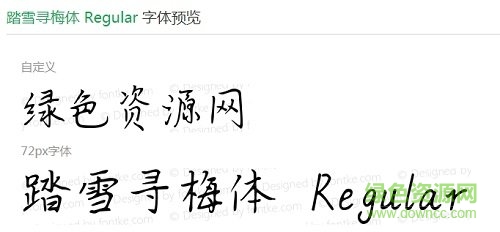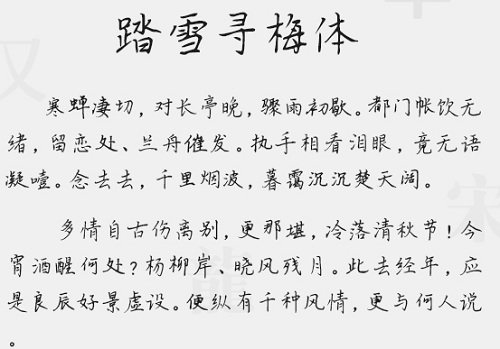
踏雪尋梅體是一款非常完整的中文簡體,采用了手寫字體和硬筆書法的藝術(shù)美感,文字端正不阿,筆畫有序而有力,閱讀清晰大氣,綠色資源網(wǎng)今日推薦!
“踏雪尋梅風(fēng)霜事,乘舟獨(dú)釣煙雨情。”——踏雪尋梅體。本字體是在國家標(biāo)準(zhǔn)簡體字庫GB2312所包含6763漢字的基礎(chǔ)上,又增加了近200常用字,已經(jīng)覆蓋了大陸99.75%的漢字使用頻率,足以滿足日常需求。
踏雪尋梅體大氣婉約,不失靈秀之美,是一款十分悅目的鋼筆字體,筆跡嚴(yán)明而遒勁挺拔,可以運(yùn)用在藝術(shù)設(shè)計(jì)、文化創(chuàng)意等場合當(dāng)中。